Mengapa Menggunakan Font Buatan Tangan?
Diterbitkan: 2022-12-06Font buatan tangan dibuat oleh desainer yang meluangkan waktu untuk membuat setiap karakter secara hati-hati dengan tangan. Proses ini menghasilkan font yang memiliki tampilan dan nuansa gambar tangan yang unik. Meskipun ada banyak program perangkat lunak yang dapat digunakan untuk membuat font, font buatan masih dibuat oleh perancang manusia menggunakan pena dan kertas. Langkah pertama dalam membuat font buatan tangan adalah membuat sketsa setiap karakter dengan tangan. Selanjutnya, perancang akan menggunakan program perangkat lunak untuk membuat sketsa menjadi vektor, yang akan mengubahnya menjadi kerangka digital. Setelah sketsa vektor selesai, perancang dapat mulai menambahkan detail dan menyempurnakan bentuk karakter. Terakhir, karakter diberi tampilan gambar tangan yang unik dengan menambahkan ketidaksempurnaan dan ketidakteraturan. Membuat font buatan tangan adalah proses yang memakan waktu, tetapi hasilnya sepadan. Font ini memiliki daya tarik dan kepribadian yang tidak dapat ditiru oleh font yang dihasilkan komputer. Jika Anda mencari font yang unik dan bergaya untuk proyek Anda selanjutnya, pertimbangkan untuk menggunakan font buatan tangan.
Font non-standar menjadi semakin umum dalam pengembangan web. Munculnya font ikon, yang merupakan font yang berisi simbol, juga menyebabkan munculnya gaya ikon. Ikon dari font ikon hanya boleh satu warna, perenderan dan perataan tidak dapat dijamin, dan ikon tidak dapat diandalkan. Jika Anda ingin melacak dan mengekspor ikon dalam jumlah besar, itu bisa menjadi tugas Sisyphean. Sangat mudah untuk membuat kumpulan ikon yang konsisten dan terpadu menggunakan ikonografi. Aturan praktis sederhana yang harus diikuti saat membuat kumpulan ikon adalah menerapkan aturan visual ke semua ikon. Semua ikon harus diubah menjadi file sva agar kami dapat membuat font ikon.
Nama kelas artboard akan digunakan untuk mengidentifikasi font ikon di kelas CSS. Seret> jatuhkan ikon yang dipilih ke dalam kumpulan SVG baru untuk langkah pertama. Setelah Anda memilih semua ikon yang ingin Anda gunakan dalam font, klik ikon yang ingin Anda gunakan. Pada langkah 3, Anda akan diminta untuk membuat font yang Anda inginkan. Pada langkah 4, Anda harus mengganti nama setiap ikon dan memasukkan karakter unicode untuk masing-masing ikon. File yang dihasilkan dapat diunduh. Anda membutuhkan beberapa saat untuk membuat font ikon pertama Anda.
Jika Anda ingin menambahkan ikon ke situs web Anda tanpa menggunakan editor vektor, menggunakan font ikon adalah solusi yang bagus. Kemungkinan dengan CSS tidak terbatas. Menggunakan Adobe Illustrator, Anda dapat melacak jumlah ikon yang terus bertambah di satu lokasi. Selain itu, sangat mudah untuk menerapkan perubahan gaya ke ikon apa pun dan kemudian mengekspornya kembali dalam waktu yang sangat singkat.
Bisakah Font Menjadi Svg?
Scalable Vector Graphics (SVG) adalah versi font baru dari format OpenType, yang menggunakan format OpenType. Karena format mesin terbang SVG , beberapa karakter bahkan dapat dianimasikan, karena dapat ditampilkan dalam berbagai warna dan transparansi berbeda.
Scalable Vector Graphics (SVG) adalah jenis grafik yang dibuat menggunakan berbagai vektor. Tujuan dari aplikasi web ini adalah untuk menyediakan solusi grafik vektor umum untuk digunakan di Internet. Font SVG akan memiliki ekstensi file ".svg", yang akan diubah menjadi XML saat dikonversi. Anda memiliki tiga opsi jika ingin teks memiliki font yang dirender di penampil SVG mana pun. Alih-alih font TTF/EOT/OTF, Anda dapat menentukan font SVG menggunakan deklarasi @Font-face CSS. Sangat mengecewakan bahwa tidak ada cara untuk menyorot font. Pembuat konten harus mempertimbangkan untuk menggunakan teknologi font alternatif jika mereka menginginkan peningkatan kualitas dan keterbacaan dalam font kecil.
Bisakah Anda Memasukkan Teks Dalam Svg?
Elemen teks dibuat dengan *teks% SVG Gradien, pola, jalur kliping, topeng, atau filter dapat diterapkan ke teks>, sama seperti jenis elemen grafis SVG lainnya. Ketika elemen teks tidak termasuk dalam elemen *text%27, itu akan dirender dalam SVG.
Pembuat Font Svg
SVG Font Generator adalah alat yang memungkinkan Anda membuat font yang dapat digunakan di web. Font yang Anda buat dapat digunakan di situs web mana pun yang mendukung penggunaan font SVG.
Ini adalah teknologi font baru yang menyertakan beberapa fitur unik. Mesin terbang SVG dapat memiliki banyak warna, pola gradien, dan jenis karakter lain sesuai keinginan. grafik vektor adalah jenis grafik yang paling umum digunakan dalam font tradisional. Garis keras pada jenis karakter ini ideal untuk karakter serif atau sans-serif biasa karena diisi dengan padat. Standar font web baru, yang dikenal sebagai SVG, telah disetujui oleh World Wide Web Consortium (W3C). Font ini juga dikenal sebagai Font Warna karena memiliki warna yang disematkan dan lebih detail daripada font standar. Selain itu, mereka menawarkan semantik bawaan seperti <title> dan <desc>, membuatnya mudah diakses oleh pembaca teks dan layar.
Buat Font Dari Svg Online
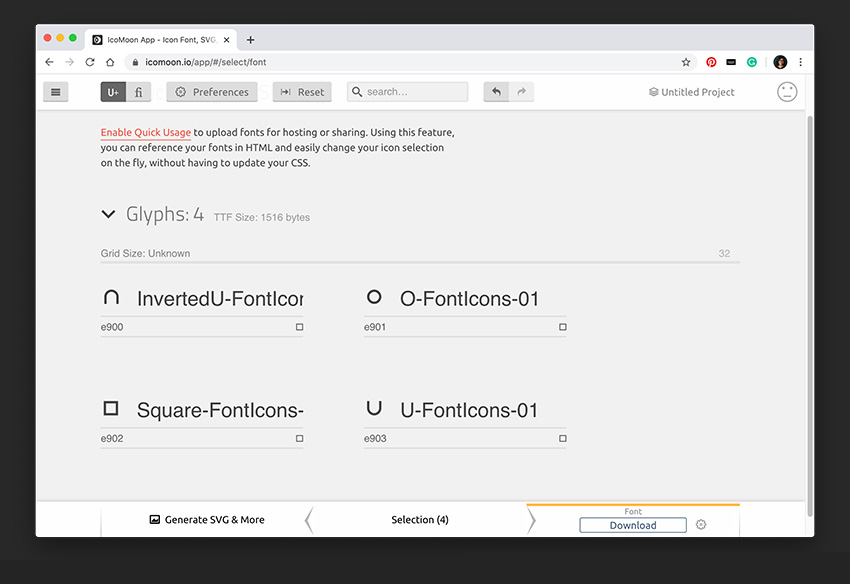
Ada banyak cara untuk membuat font dari file svg online. Salah satu caranya adalah dengan menggunakan layanan seperti Adobe Fonts atau Font Squirrel. Cara lain adalah dengan menggunakan alat seperti Font Forge.
Bagaimana saya bisa mengonversi vg ke font? Anda dapat mengimpor setiap mesin terbang SVG khusus Anda dengan mengeklik tombol Ikon Impor berwarna ungu di sudut kanan atas halaman. Anda dapat mengubah mesin terbang di font dengan mengklik tombol Hasilkan Font di bagian bawah halaman. Anda mungkin dapat menemukan mesin terbang Anda dengan menggunakan program seperti Peta Karakter GNOME (untuk Linux) atau Peta Karakter Windows atau Palet Karakter Mac OS. Periksa apakah cache font sistem Anda dibersihkan setelah menginstal font baru.
Format Berbeda Untuk Font Svg Di Browser
Ini berarti Anda dapat menggunakan font SVG saat membuat dokumen Anda. Jika Anda ingin menggunakan font SVG di Firefox atau Chrome, Anda harus membuatnya dalam format yang berbeda. Firefox, seperti Chrome, mendukung FONT.
Ada beberapa batasan dalam menggunakan font SVG. Mereka tidak kompatibel dengan penggunaan font yang sama dalam dokumen seperti font lainnya, dan mungkin tidak didukung oleh semua browser. Kabar baiknya adalah jika Anda ingin menggunakan font sva di proyek berikutnya, Anda sudah mendapatkannya.
Mengapa Menggunakan Ikon Svg?
Ada beberapa keuntungan menggunakan ikon sva . Mereka juga berbasis vektor, memungkinkan mereka untuk diperkecil atau diperbesar tanpa kehilangan kualitas. Anda dapat memuatnya di situs web Anda karena itu adalah file yang sangat kecil. Akhirnya, mereka dapat disematkan dalam HTML dan CSS hanya dalam beberapa baris kode menggunakan berbagai bahasa pemrograman yang berbeda.